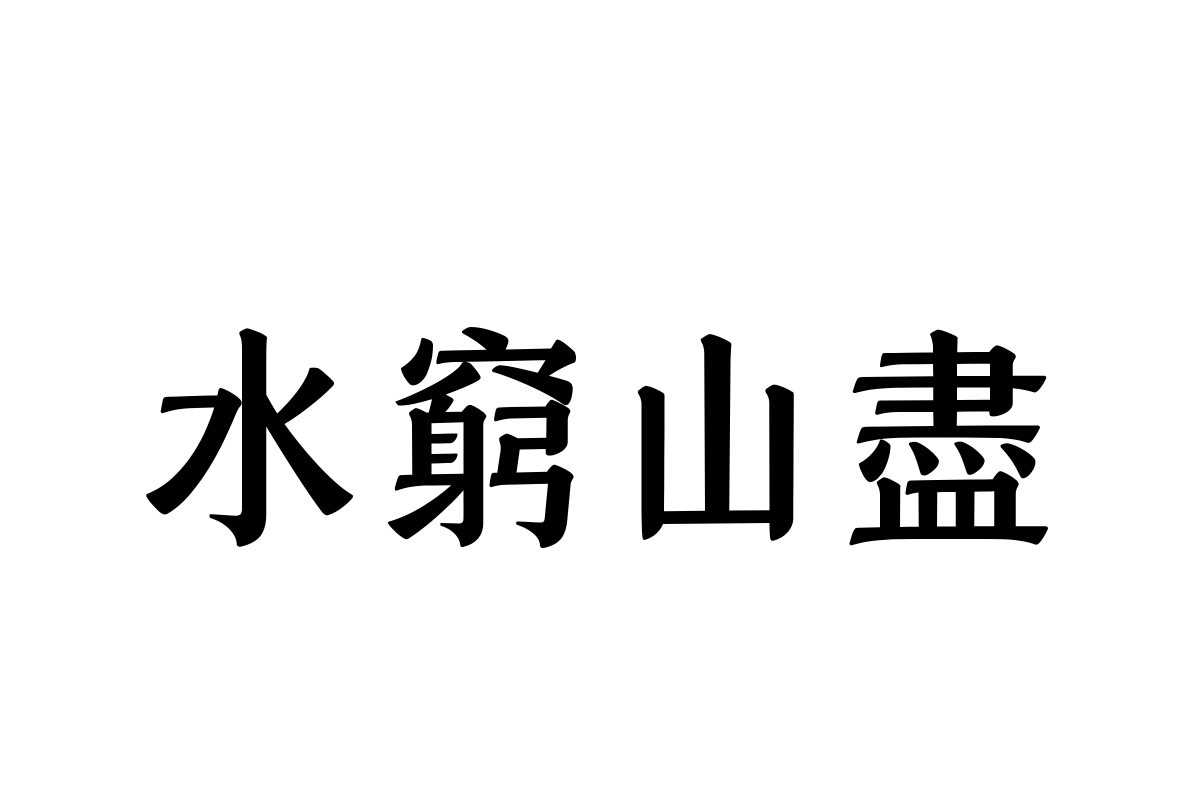
汉仪永字夏蝉65f是一款具有独特风格的中文字体,其特点是笔画流畅、结构紧凑、字形饱满。这款字体的线条粗细适中,给人一种优雅而有力的感觉,适合用于各种需要强调文字的地方。同时,它的字形也具有一定的艺术感,能够吸引人们的眼球,让人过目不忘。总的来说,汉仪永字夏蝉65f是一款非常实用的中文字体,无论是在印刷品还是电子屏幕上都能够展现出其独特的魅力。